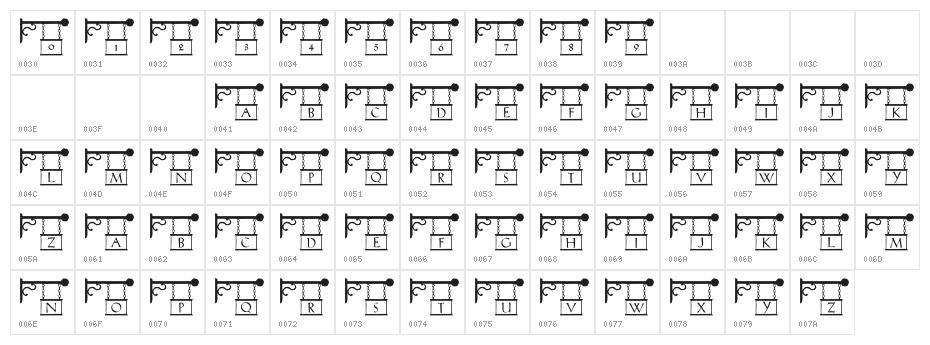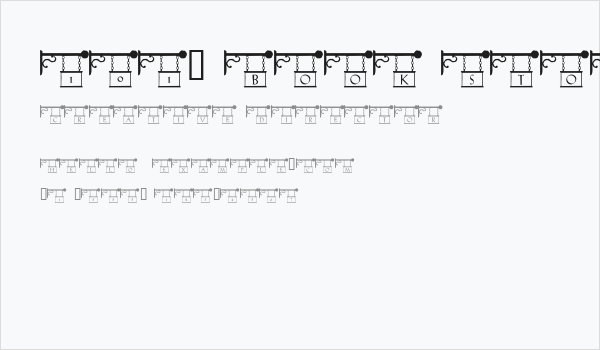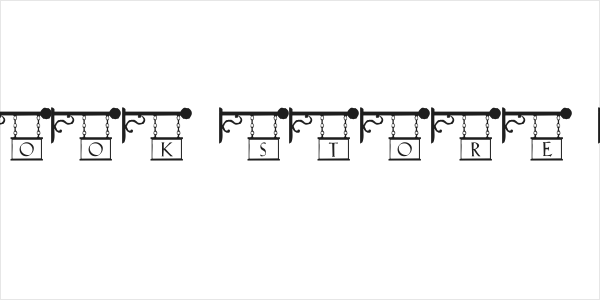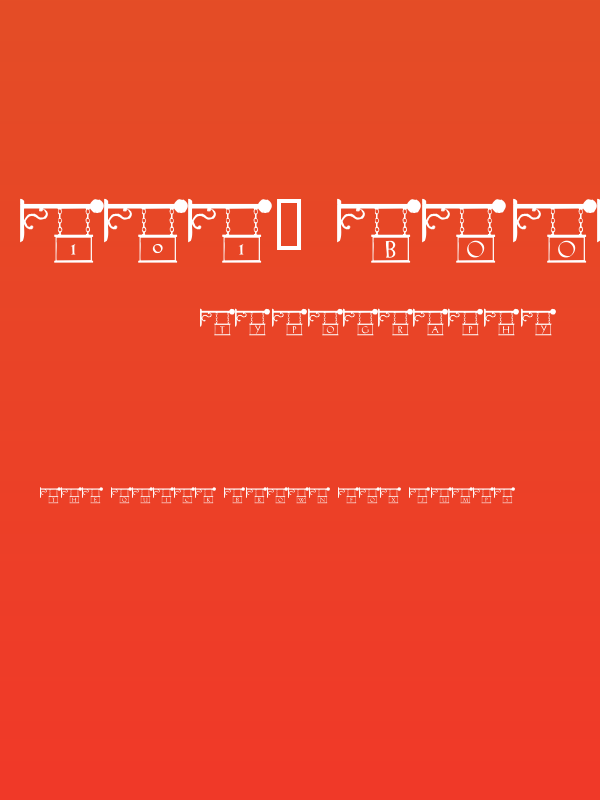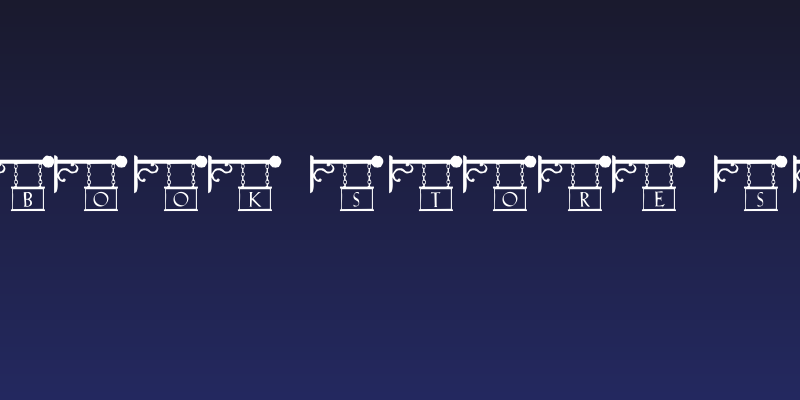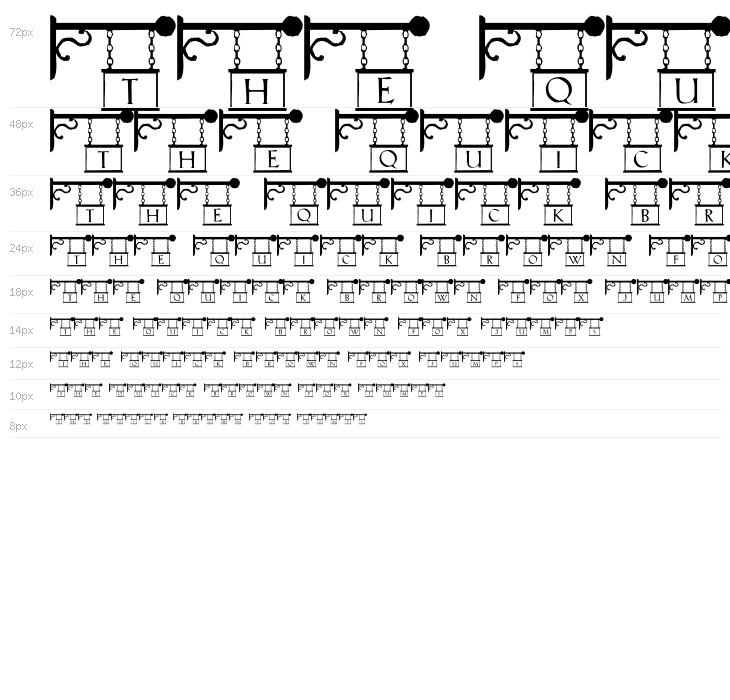
101! Book Store SignZ Font
| Cas d'utilisation | Logos, Headlines, Decorative text |
| Projets proposés | Ideal for vintage-themed branding, shop signs, invitations, and decorative posters. |